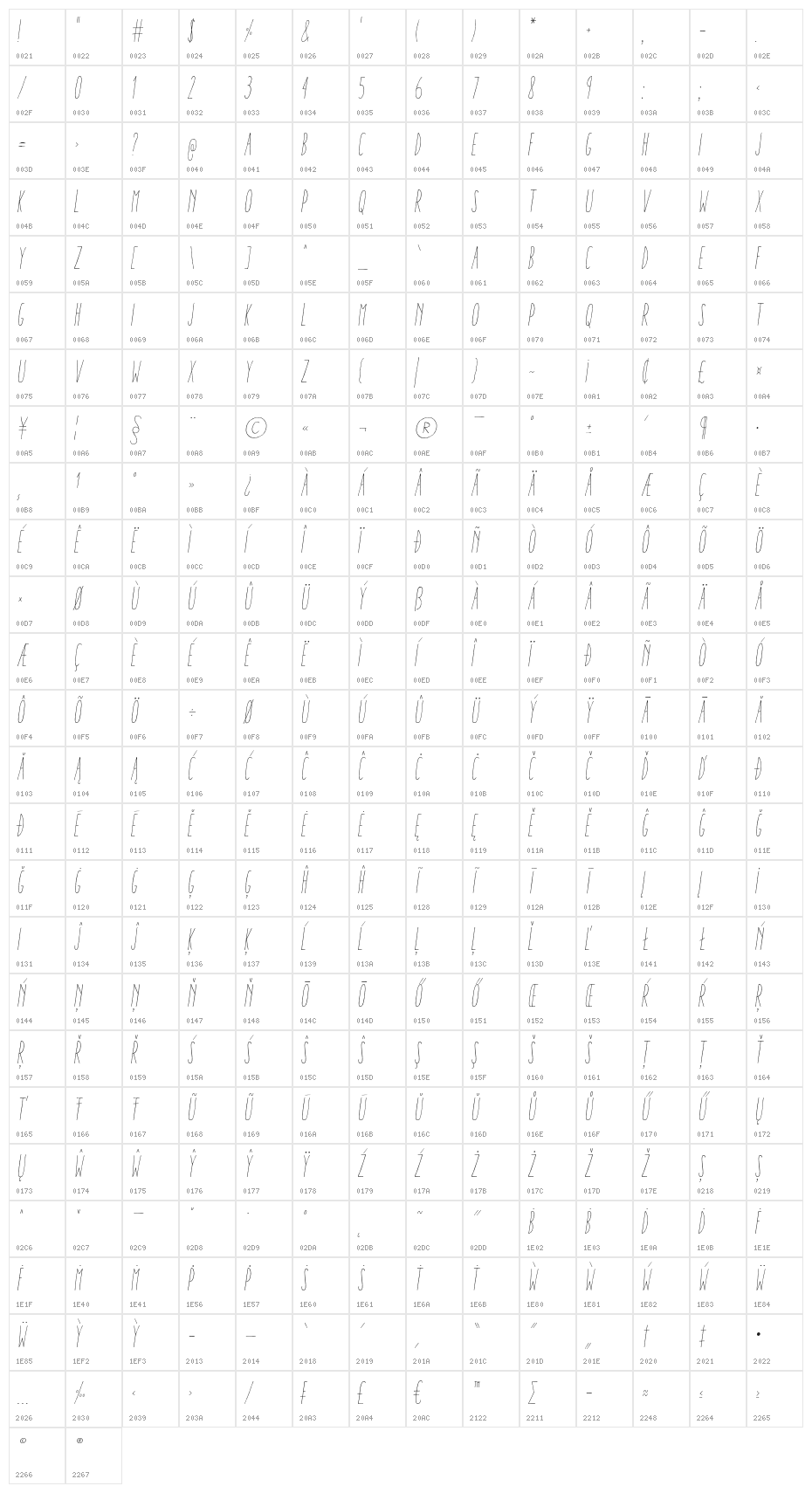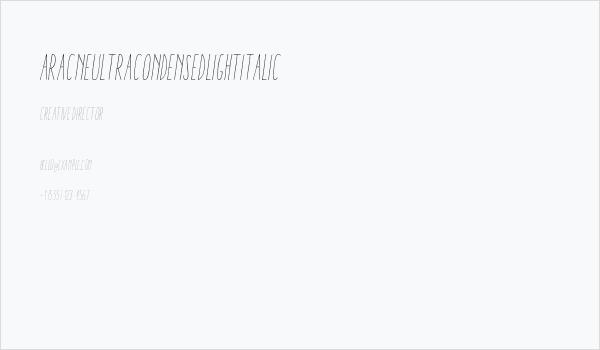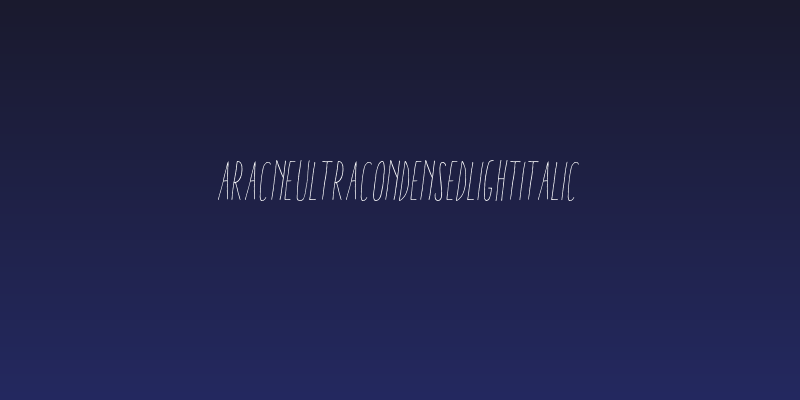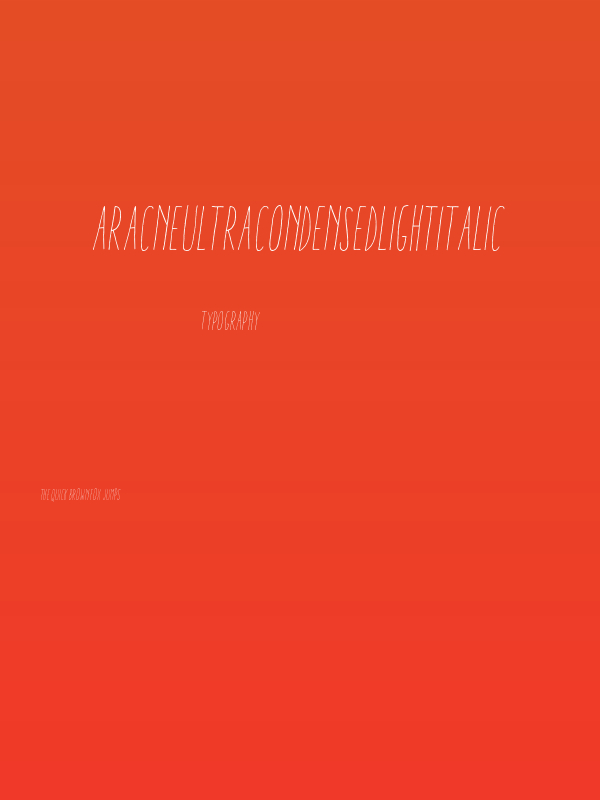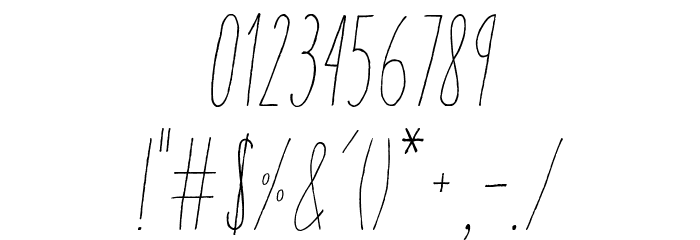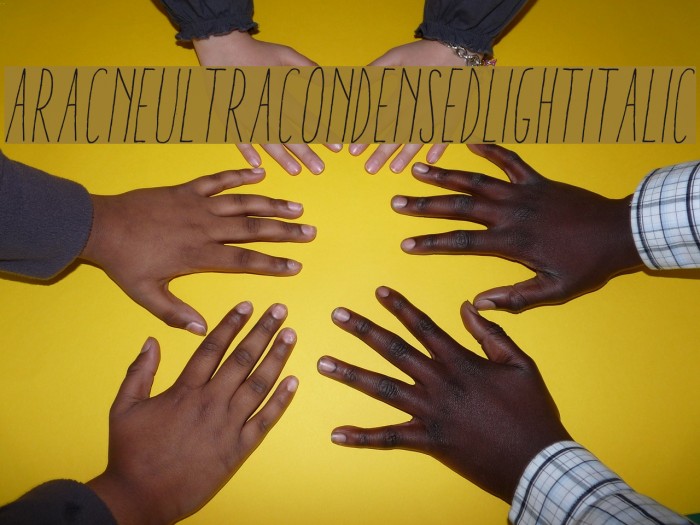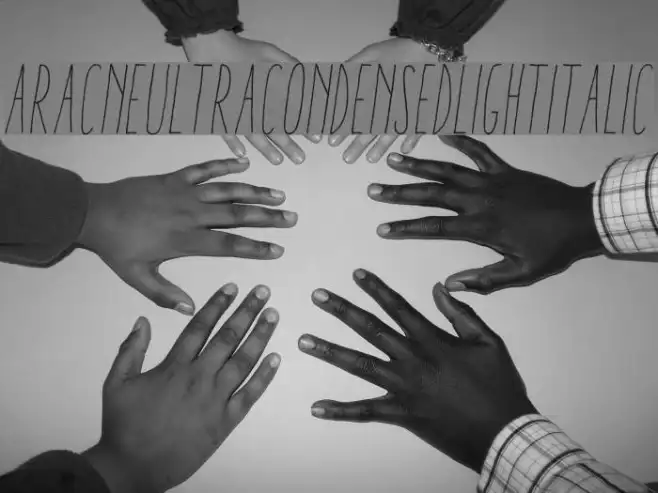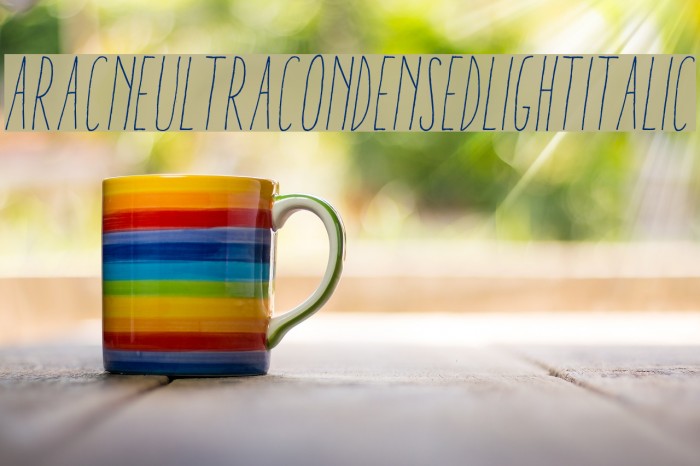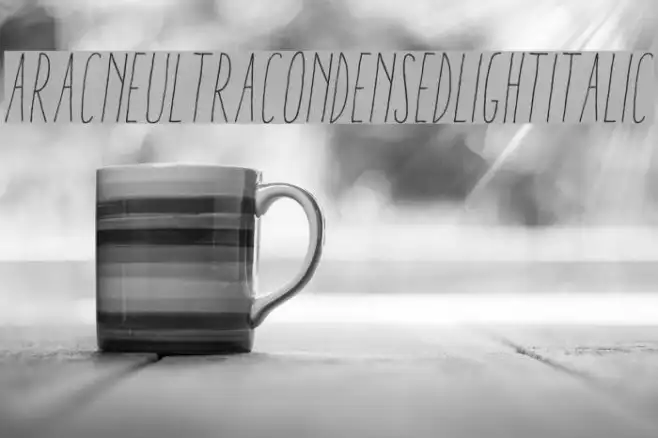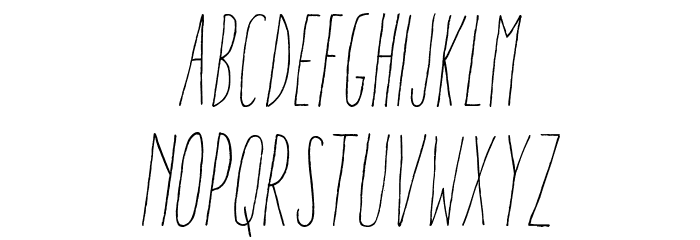
AracneUltraCondensedLightItalic Font
✎ Modern
| Vorgeschlagene Projekte | Ideal for fashion magazines, modern branding, elegant invitations, and minimalist posters. |